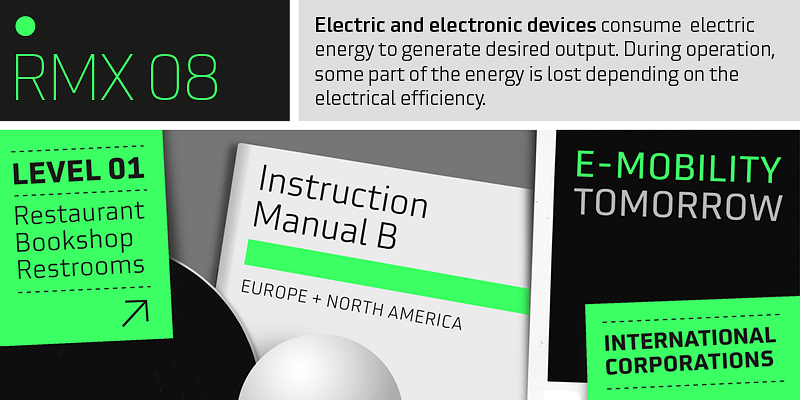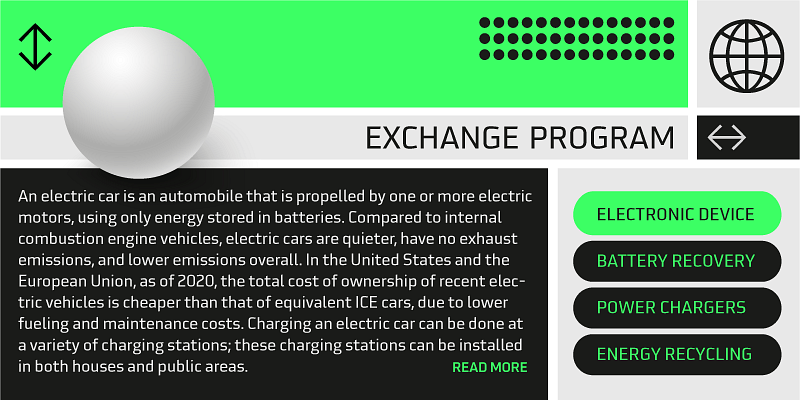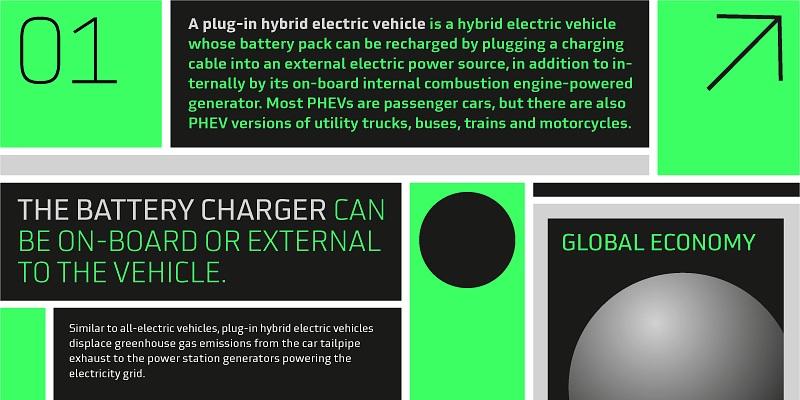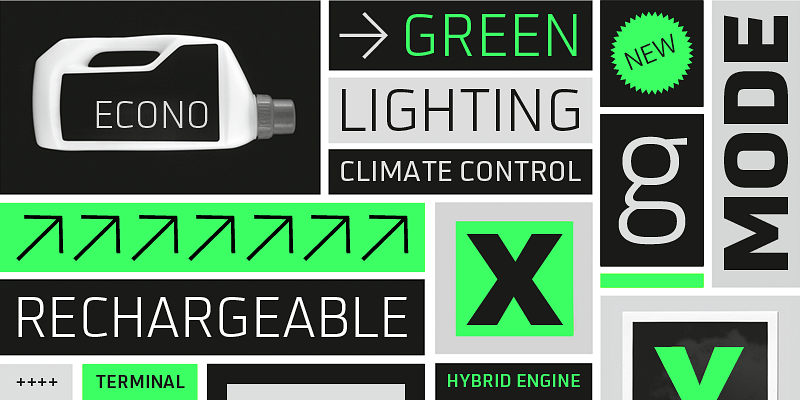
Der Stil von Utility ist von konstruierten, industriellen und rationalen Schriften wie Eurostile oder DIN 1451 inspiriert. Die Superellipsenstruktur der Kurven verleiht dieser Schrift das typisch technische Aussehen, jedoch mit einer leicht humanistischen Note. Diese humanistische Note wurde durch die Abkehr vom konstruktionsbasierten Modell durch handschriftliche Motive erreicht. Beispielsweise bricht der ausgehende Strich beim Kleinbuchstaben „e“ aus dem Raster und verleiht der Buchstabenform etwas Dynamik.
Indem er die Endstriche öffnet, lässt er die Zeichen atmen und verbessert ihre Lesbarkeit. Die Familie verfügt über 7 Schriftstärken und eignet sich ideal für Film und Fernsehen, Redaktion und Verlagswesen, Logos, Branding und Corporate Design sowie Sport. Utility bietet erweiterte typografische Unterstützung mit Funktionen wie Ligaturen; alternativen Zeichen; Formen, bei denen die Groß- und Kleinschreibung beachtet wird; Brüchen; hoch- und tiefgestellten Zeichen sowie stilistischen Alternativen. Sie wird mit Kapitälchen und einer kompletten Auswahl an Ziffernsatzoptionen geliefert – Mediäval- und Versalziffern, jeweils in tabellarischer und proportionaler Breite.